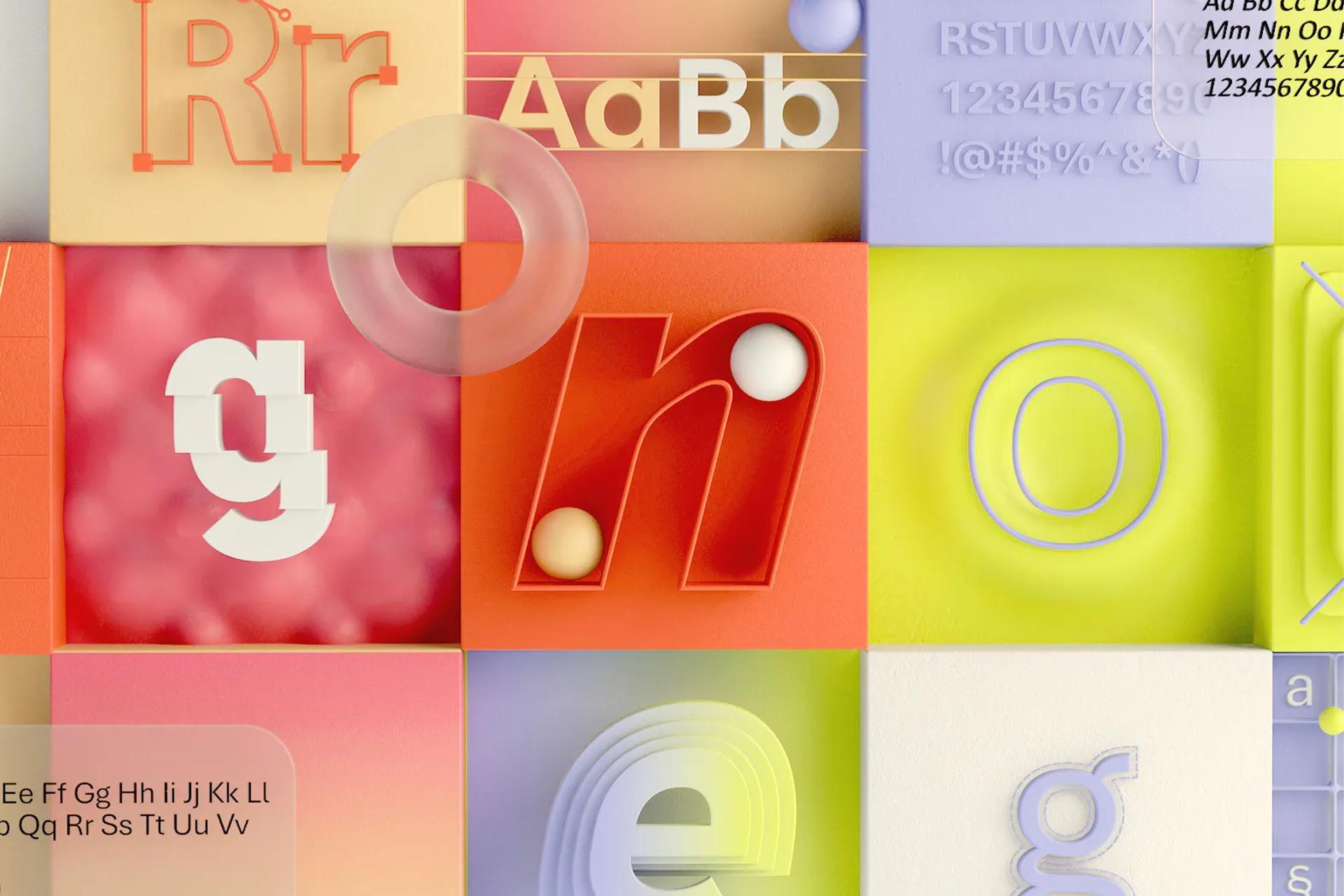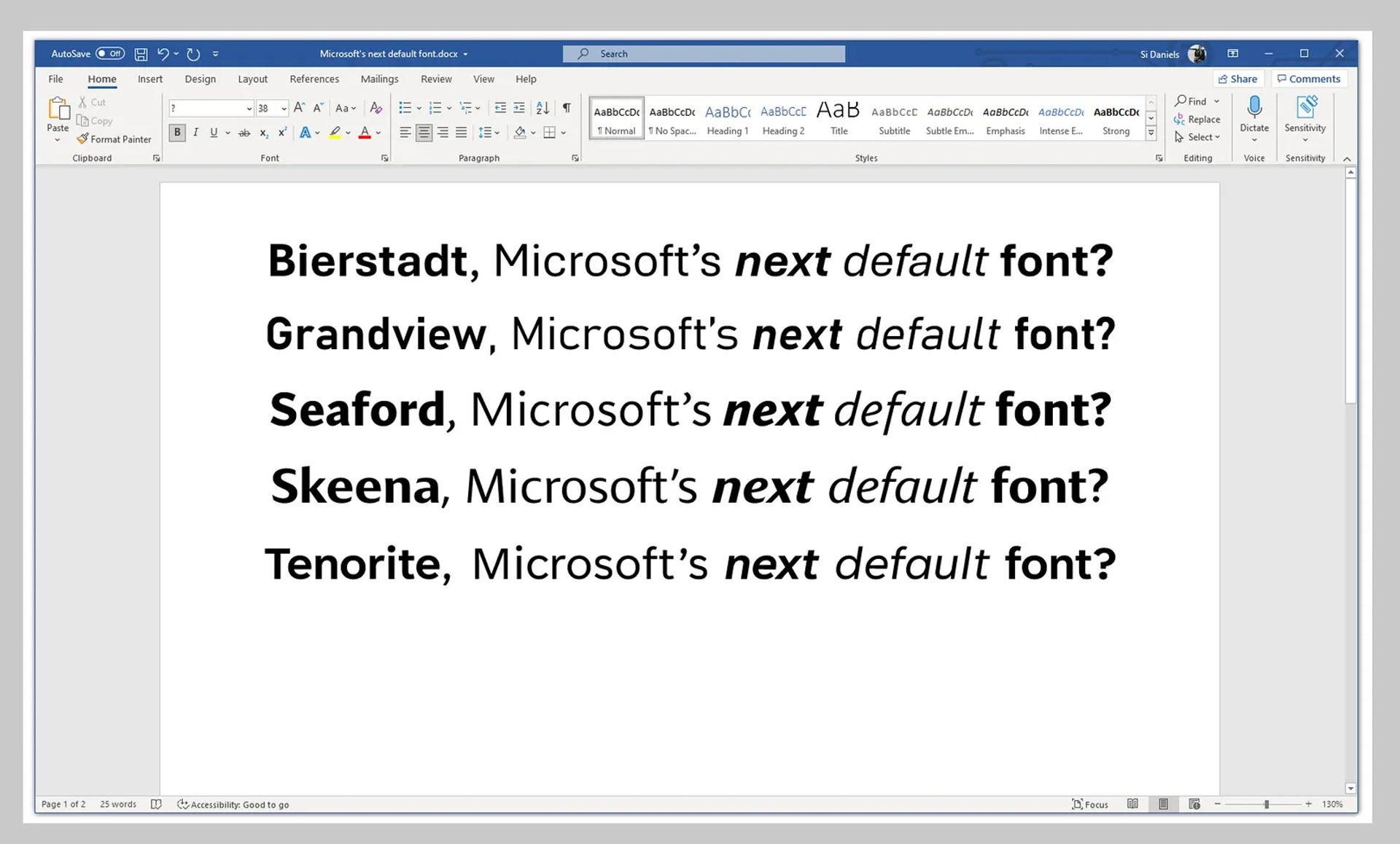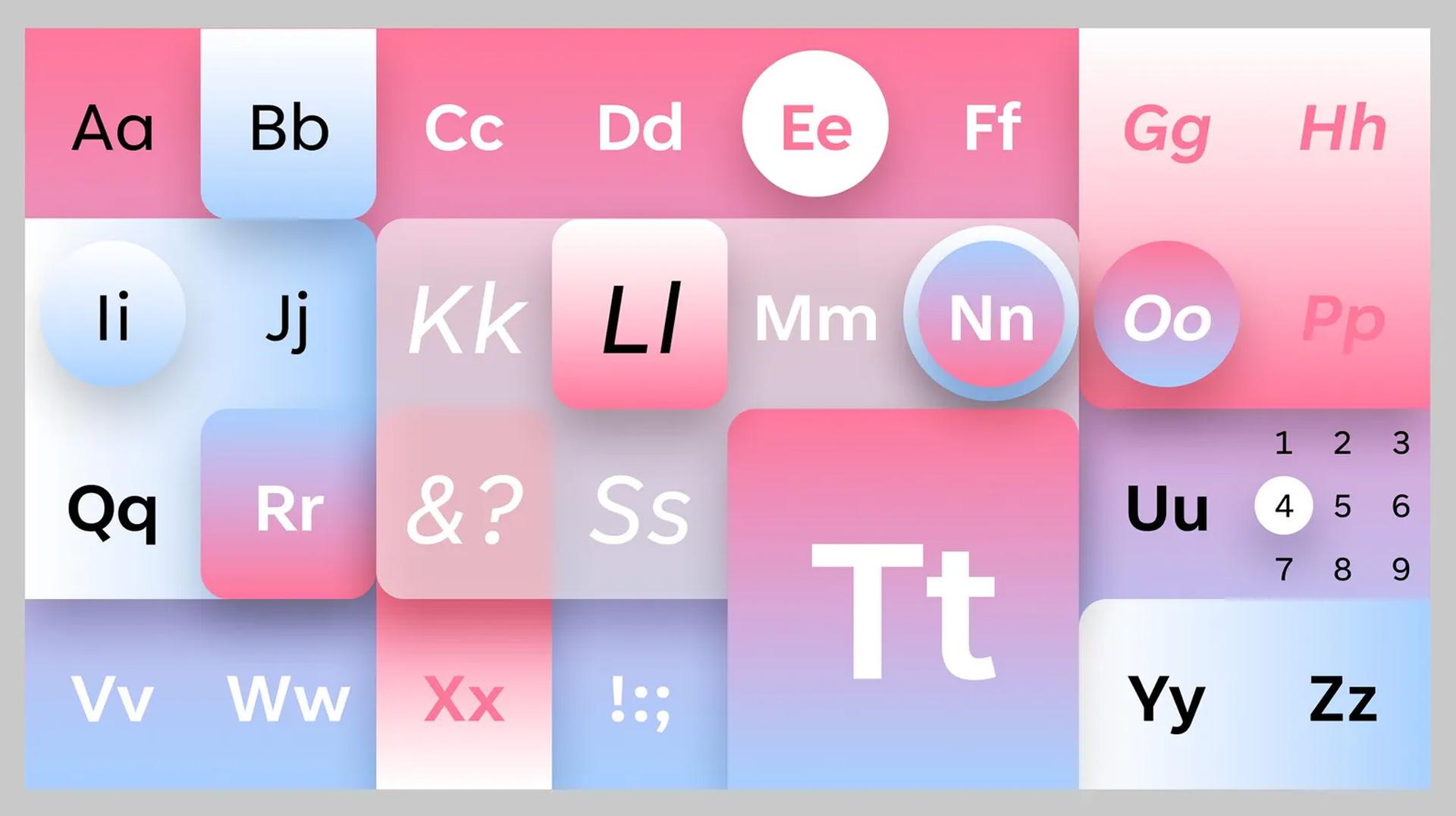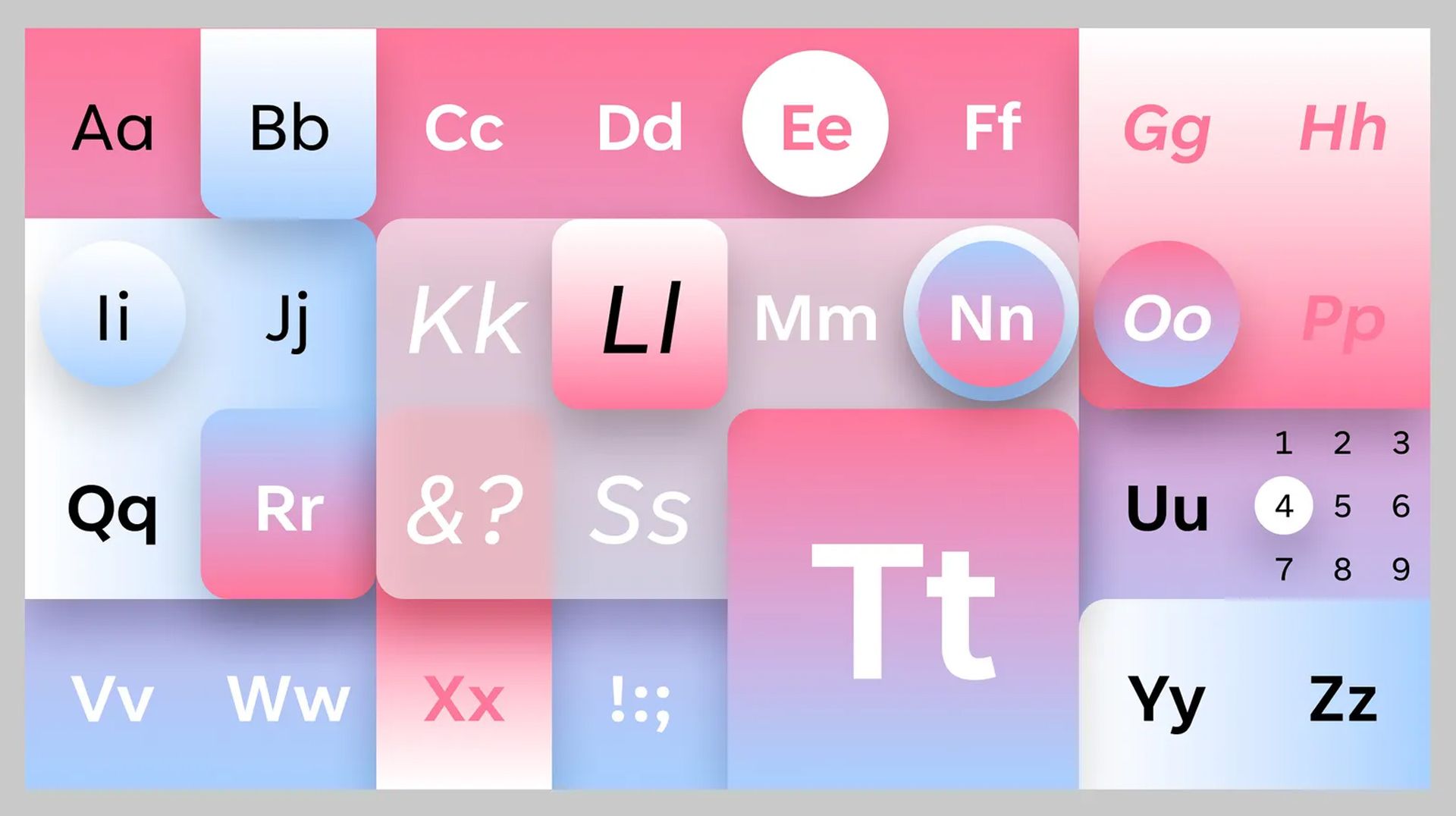
مایکروسافت پس از حدودا ۱۵ سال میخواهد کالیبری، فونت پیشفرض سرویسهایش را عوض کند. طراح کالیبری در مصاحبهای جالب با وایرد میگوید از این اتفاق آسودهخاطر است.
بهمدت تقریبا ۱۵ سال کالیبری (Calibri) فونت پیشفرض و غالب سیستمهای مایکروسافت بوده است. این فونت بارهاوبارها در فایلهایی از ورد و پاورپوینت و اکسل ظاهر شده که فرمتشان بدون تغییر بوده است. بااینحال، مایکروسافت تصمیم گرفته است فونت پیشفرضش را به عضو جدید فونتهای سری سنس سریف بهروزرسانی کند. بهنوشتهی وایرد، مایکروسافت رسما اعلام کرده است فونت پیشفرض کالیبری را با یکی از پنج فونتی جایگزین میکند که هفتهی گذشته منتشر کرده است.
انتخاب فونت پیشفرض جدید پایان دورانی بلندمدت برای کالیبری محسوب میشود؛ ولی لوکاس دگروت، طراح کالیبری، از این اتفاق ناراحت نیست و آن را احساس آسودهخاطری توصیف میکند. دگروت فونت کالیبری را اوایل دههی ۲۰۰۰ بهعنوان بخشی از مجموعهفونت جدیدی با هدف بهبود خوانایی صفحهنمایش طراحی کرد. او در مصاحبه با وایرد میگوید فونت را با عجله طراحی کرده است و از قبل طرحهایی دردسترس داشته و گوشههایی گِرد به آنها اضافه کرده است تا طراحی نهایی را جذابتر کند.
مدتی طولانی صفحهنمایش کامپیوترها از تراکم پیکسلی کافی برای رندر تمامی فونتها برخوردار نبود و روی این صفحهنمایشها گوشهی گِرد به فرم قوسمانند دیده نمیشدند. سال ۲۰۰۰ بهلطف فناوری جدید ClearType مایکروسافت، وضعیت برای فونتها تغییر کرد. ClearType وضوح نمایشگرهای LCD را بهینه کرد و باعث شد فونتهایی نظیر کالیبری راحتتر خوانده شوند. مایکروسافت بهحدی به کالیبری علاقهمند شد که سال ۲۰۰۷ از آن بهعنوان فونت پیشفرض ویندوز ویستا استفاده کرد.
فونت اساسا مثل لباسی برای ایدهها است و کالیبری دیگر نمیتواند بیانگر ایدههای مایکروسافت باشد
از آن زمان تاکنون، کالیبری با فروتنی تمام همهی وظایفش را انجام داده است. کالیبری برخلاف فونتهایی نظیر هلوتیکا، به استانداردی برای چاپ محتوا تبدیل نشد و رقبای زیادی نیز برای خود ایجاد نکرد. سایمون دنیلز، مدیر برنامهی اصلی واحد طراحی مایکروسافت آفیس، میگوید معمولا مشتریان بعد از مدتی علیه فونتها موضع میگیرند؛ اما چنین اتفاقی برای کالیبری رخ نداد.
بهگفتهی دنیلز، کالیبری هیچ مشکلی ندارد و این گفته حتی پس از دو دهه از طراحی این فونت صدق میکند. بااینحال، دنیلز سرانجام به این نتیجه رسید که زمان استفاده از فونتی جدید فرارسیده است. مایکروسافت بهجای اینکه بهسرعت سراغ فونت جدیدی برود، زمان کافی به خودش میدهد تا گزینهها را بهخوبی بررسی کند و درنهایت بهینهترین فونت را به فونت پیشفرض تبدیل کند.
دنیلز از طراحان برجسته درخواست کرد پنج فونت طراحی کنند. هر یک از این پنج فونت رویکرد متفاوتی دارند: فرم فونت تنورایت موجدار و دایرهای و علائم نگارشیاش مدور است؛ فونت بیرستَت سادهتر است و به تایپوگرافی قدیمی سوئیس ادای احترام میکند؛ اسکینا نسخهی «انساندوستانهی» سنس سریف است؛ گرندویو فونتی «صنعتی» محسوب میشود؛ و سیفورد از فرم صندلیهای راحتی الهام میگیرد: راحت، اما ارگونومیک.
مایکروسافت از مردم میخواهد تا بگویند کدام فونت برای جایگزینی با کالیبری بهتر است
تمامی پنج فونت جدید هماکنون برای استفاده در سرویسهایی از مایکروسافت دردسترس قرار دراند که به سرورهای ابری متصلاند. مایکروسافت از کاربرانش میخواهد دیدگاهشان دربارهی این فونتها را بیان و اعلام کنند به کدام فونت بیشتر علاقهمندند. دنیلز میگوید بهخاطر نمیآورد مایکروسافت قبلا با این روش فونتهایش را آزمایش کرده باشد؛ ولی اعتقاد دارد چنین روشی به تصمیمگیریِ بهتر منتهی میشود و کمی فشار کار را کم میکند.
کالیبری هیچ مشکلی ندارد؛ اما فونتی تجملی نیست
برخلاف تصور دیگران، کاربران اهمیت زیادی برای فونتها قائل هستند و از همین حالا نظردهی دربارهی فونتهای جدید را در شبکههای اجتماعی آغاز کرده و تقریبا برای تمامی فونتهای جدید نظرهای ریزبینانهای دادهاند.
فونت تنورایت
گروهی از کاربران نگراناند برخی از فونتهای جدید مایکروسافت برای افراد کمبینا یا مبتلا به خوانشپریشی خوانا نباشند و گروهی دیگر انتقاد کردهاند چرا مایکروسافت بهدنبال پیادهسازی فونتی جدید در سیستمهایش است. دیگر طراحان میگویند کالیبری در هدفی که برایش طراحی شده بود، بهخوبی جواب پس داد؛ اما اکنون که تراکم پیکسلی صفحهنمایش مشکلساز نیست، فونت پیشفرض میتواند آزادیهای بیشتری داشته باشد.
توبیاس فررجونز، مدیر طراحی در Frere-Jones Type و خالق سیفورد میگوید: «فکر میکنم کالیبری بیشازحد متراکم است.» فونت جدید سیفورد فاصلهی بیشتری بین حروف قرار میدهد و از اَشکال برجستهتر استفاده میکند. در این فونت، حرفهای گِرد گِردتر هستند و حرفهای گوشهدار گوشهدارتر شدهاند تا کلمات در جمله متمایزتر بهنظر برسند.
دگروت میگوید از برخی از فونتهای جدید مایکروسافت متعجب شده است و بیشتر از همه به سیفورد علاقهمند است؛ چون صدای محکمی دارد؛ البته صدای محکم در طراحی ممکن است خطرناک باشد. او بیان میکند: «یکی از کارهایی که تلاش کردم در کالیبری انجام دهم، این بود که فونت را بهنوعی بیطرف جلوه دهم.»
اکثر کاربران عادی ممکن است درکی از «صدای محکم» طراحی فونت نداشته باشند یا حتی متوجه نشوند فونت پیشفرضشان عوض شده است. در توییتر تعدادی از کاربران به مایکروسافت گفتهاند تفاوتهای بین پنج فونت جدید را نمیتوانند تشخیص دهند.درمقابل، طراحان میگویند هر یک از پنج فونت جدید با طراحی متفاوتی همراه شدهاند و در نحوهی ارتباط آنلاین مردم میتوانند تفاوت ایجاد کنند.